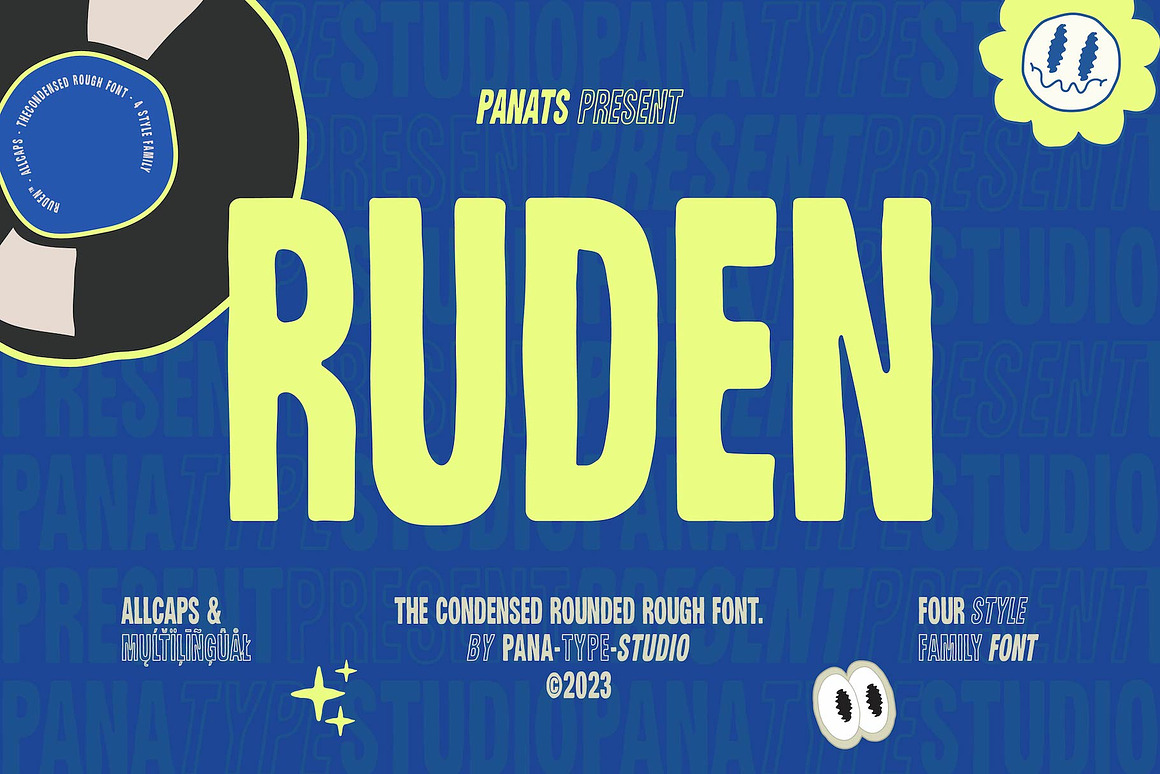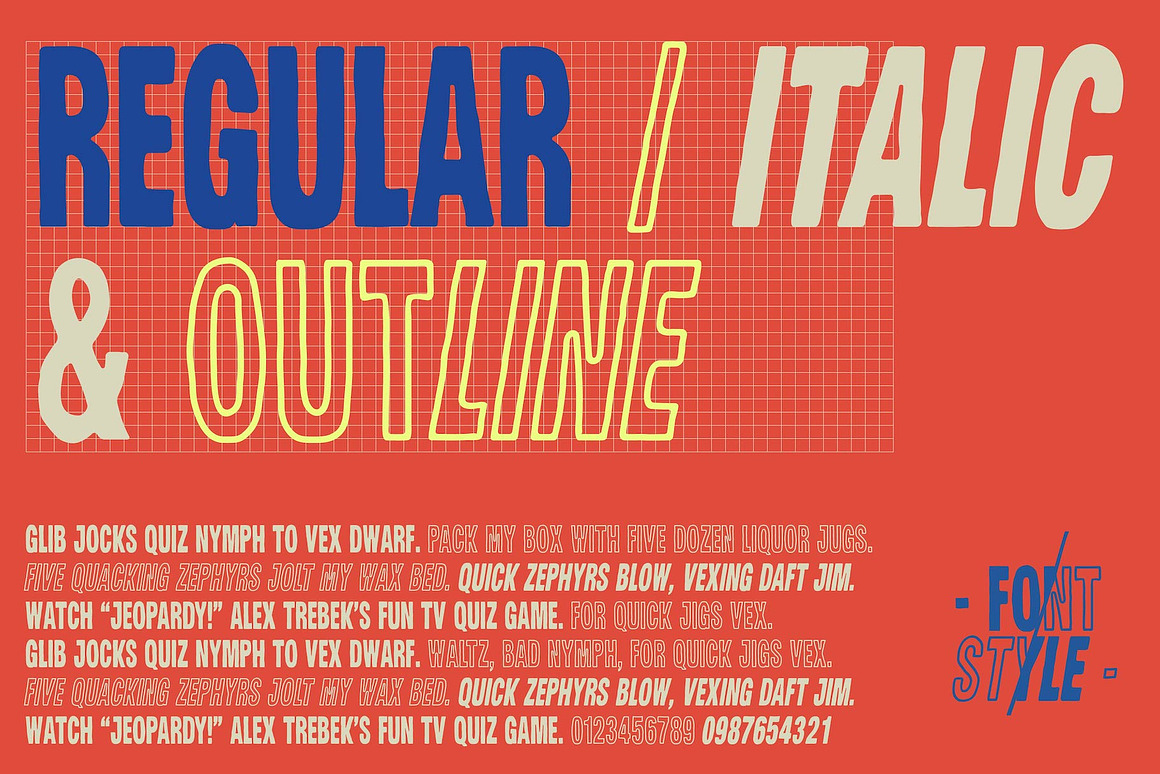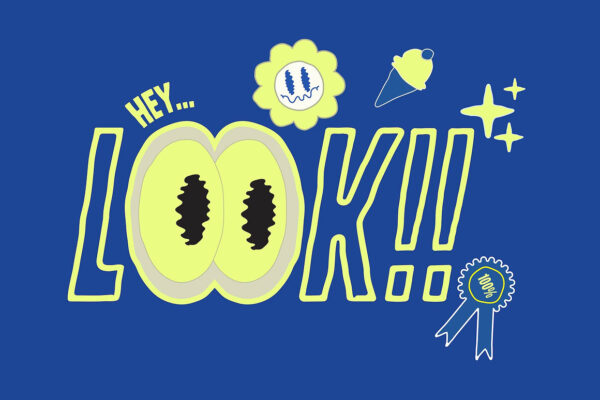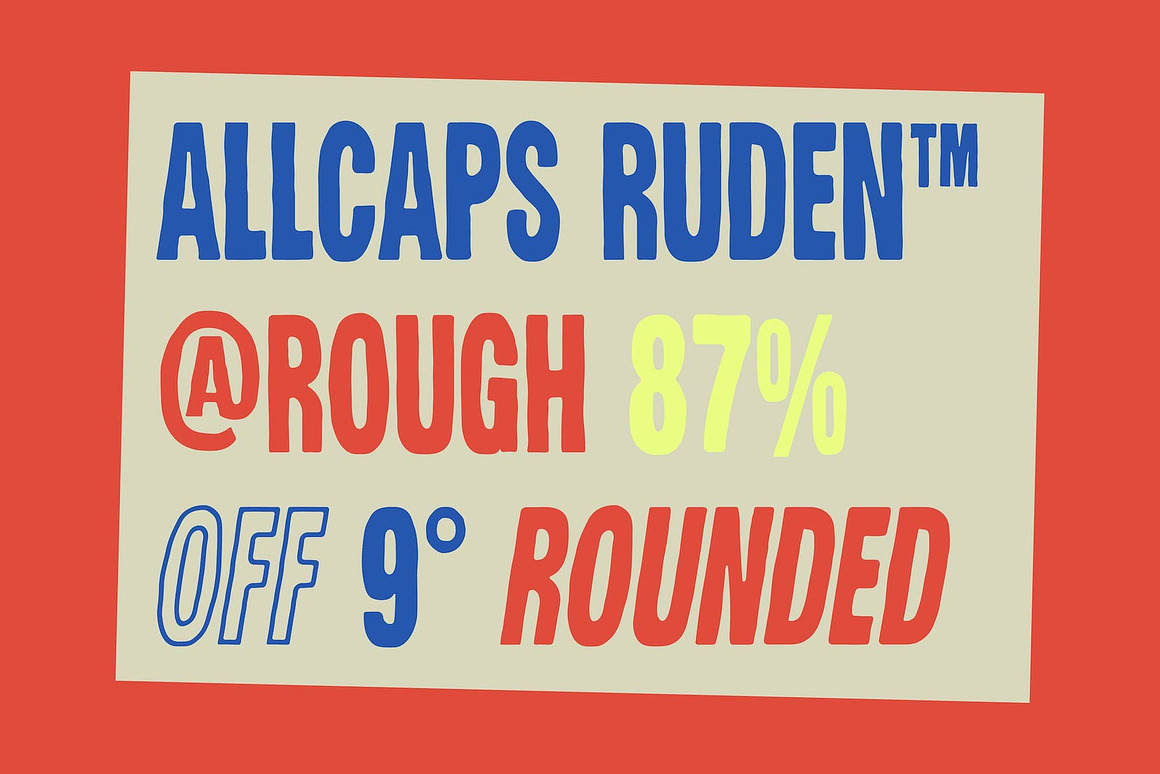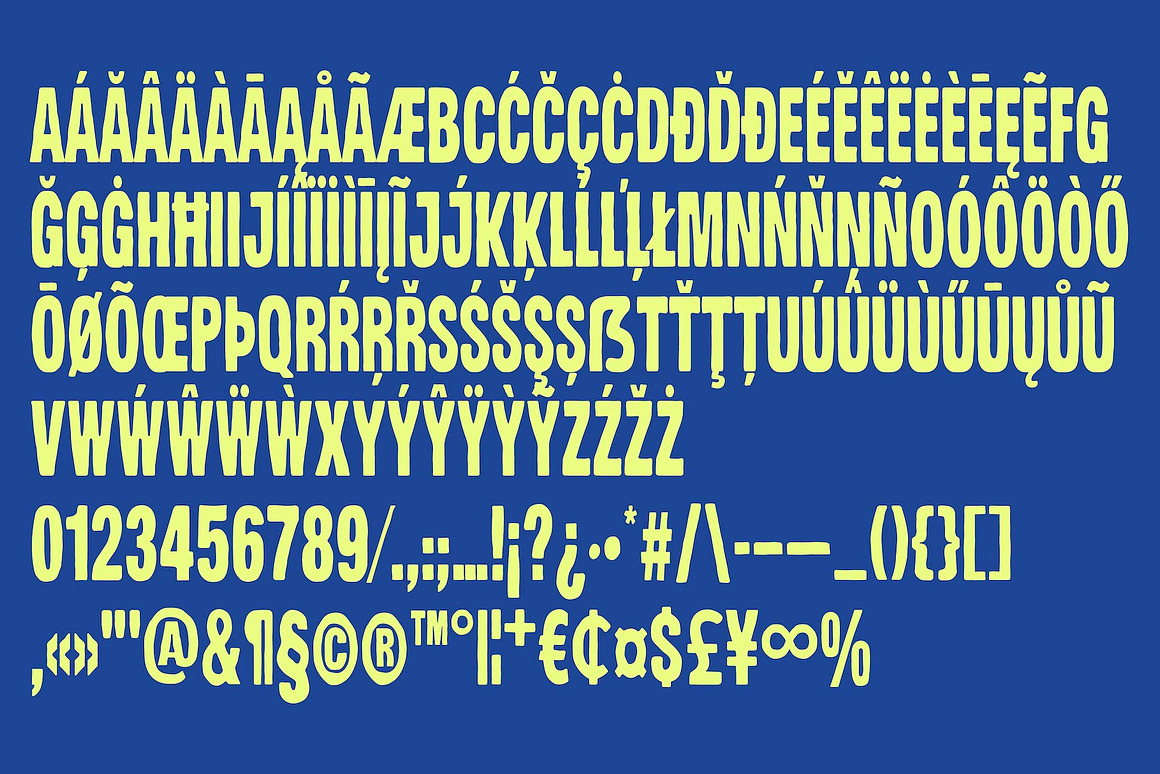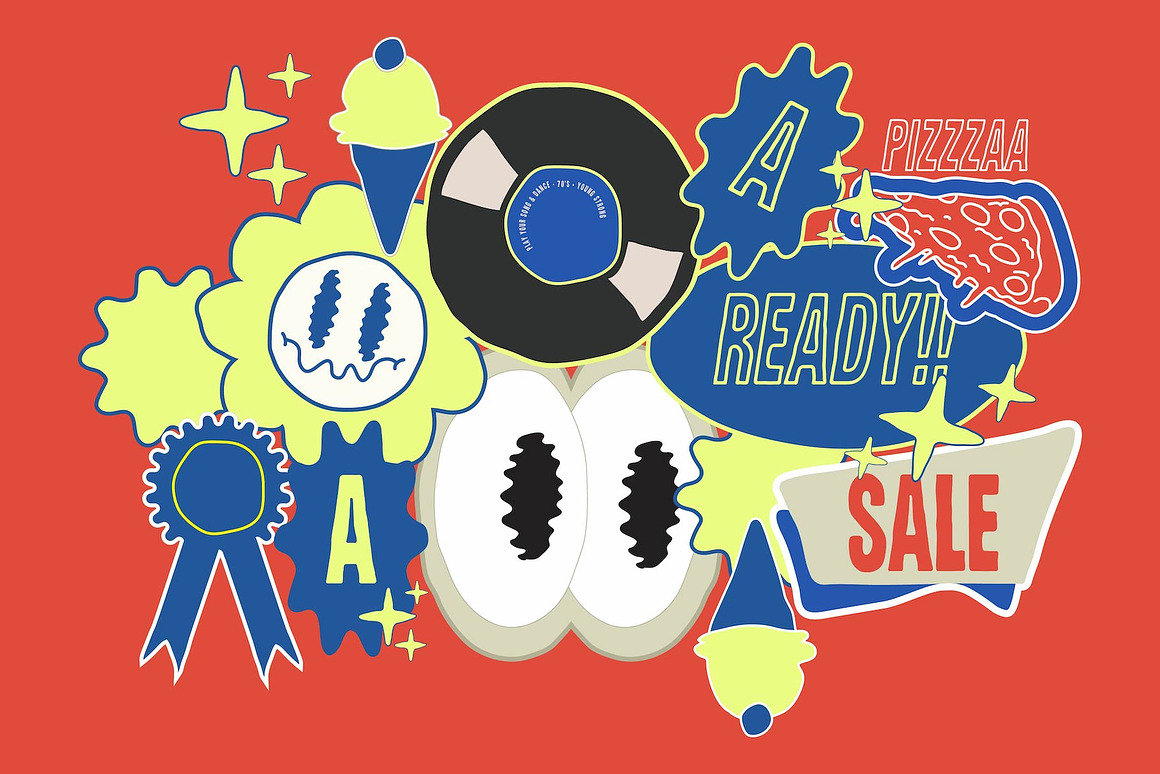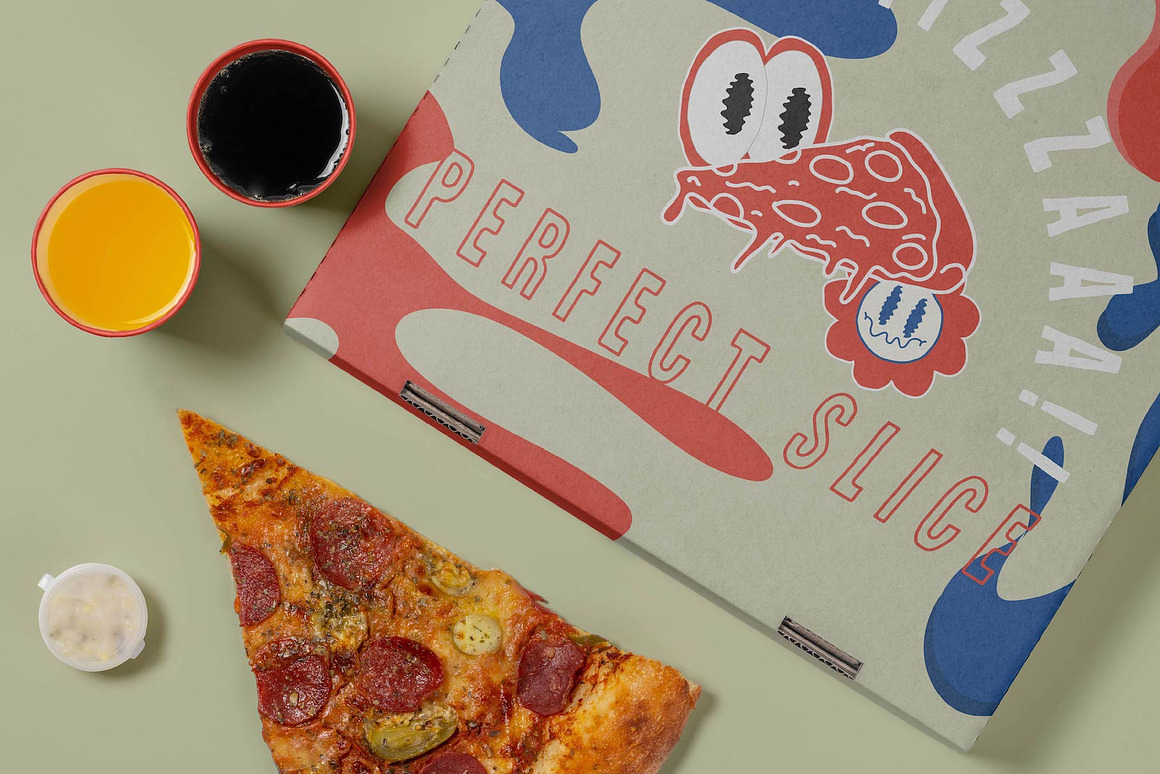
RUDEN Display Font
RUDEN – Font Display Bergaya Kasar yang Elegan dan Modern Vintage
RUDEN adalah jenis huruf display dengan gaya bulat dan padat, bertekstur kasar namun tetap terlihat organik layaknya tulisan tangan. Tersedia dalam 4 variasi gaya: Regular, Italic, Outline, dan Outline Italic, font ini dirancang khusus untuk mendukung berbagai kebutuhan desain grafis Anda—mulai dari tampilan vintage modern, nuansa elegan, hingga gaya kasual yang lembut namun berkarakter.
Font ini sangat cocok digunakan untuk branding, logo, poster, kemasan produk, undangan, serta proyek kreatif lainnya yang membutuhkan sentuhan unik dan estetika yang dirancang dengan detail.